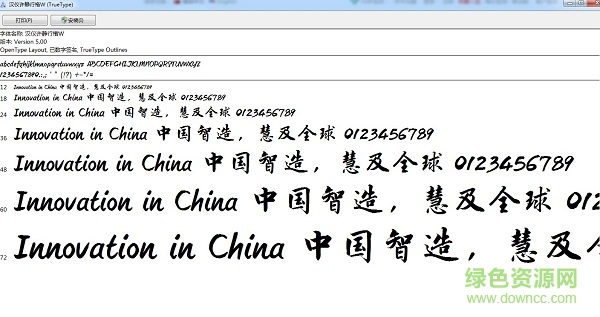
漢儀許靜行楷字體
漢儀許靜行楷w字體是一款蘊(yùn)含古典氣息的行楷字體,線條流暢,結(jié)構(gòu)端正,字形優(yōu)美,影視海報(bào)、招牌設(shè)計(jì)、古籍封面等均可使用該字體,有需要者歡迎免費(fèi)下載!
行楷字體特點(diǎn)
漢字的一種書(shū)體,是行書(shū)與楷書(shū)的結(jié)合,一般的理解是字中楷多行少,是借鑒行書(shū)筆法的楷書(shū),其最大特點(diǎn)是在楷書(shū)結(jié)構(gòu)的基礎(chǔ)上融入行書(shū)的連帶筆法。變端莊嚴(yán)肅為活潑跳動(dòng),但基本不作過(guò)多的簡(jiǎn)省,大致保持楷書(shū)風(fēng)貌。
漢儀許靜行楷w